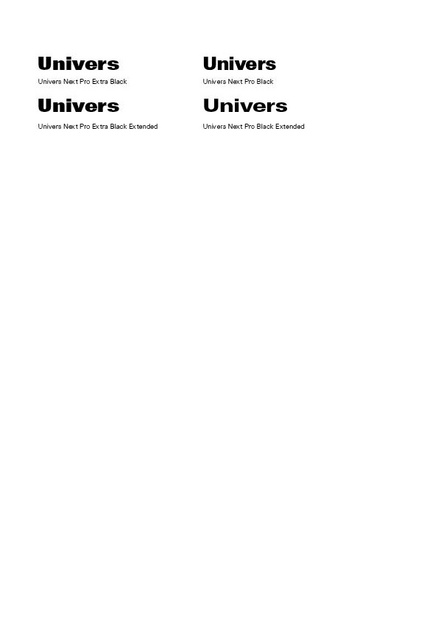
Univers Extended Extra Black vs Extra Black
ich habe vor ein paar Tagen, die Nuztungsrechte für 2 Schrifte erworben: Univers Extended Extra Black und Extra Black. Ich bin zwar immer noch ein Neuling, würde aber behaupten, dass ich ein bisschen unterscheiden kann zwischen einem Extended und nicht extended Schnitt. Allerdings finde ich hier leider keinen Unterschied. Bin ich zu unerfahren um den Unterschied zu erkennen?
danke für die Antwort. Meine Frage bezog sich auf die Bilder die ich hochgeladen habe. Also Univers Next Pro Extended Extra Black und Univers Next Pro Extra Black im Angebot von Linotype.
Ich merke einen deutlichen Unterscheid zwischen Black und Extended Black. Aber nicht zwischen Extended Extra Black und Extra Black...